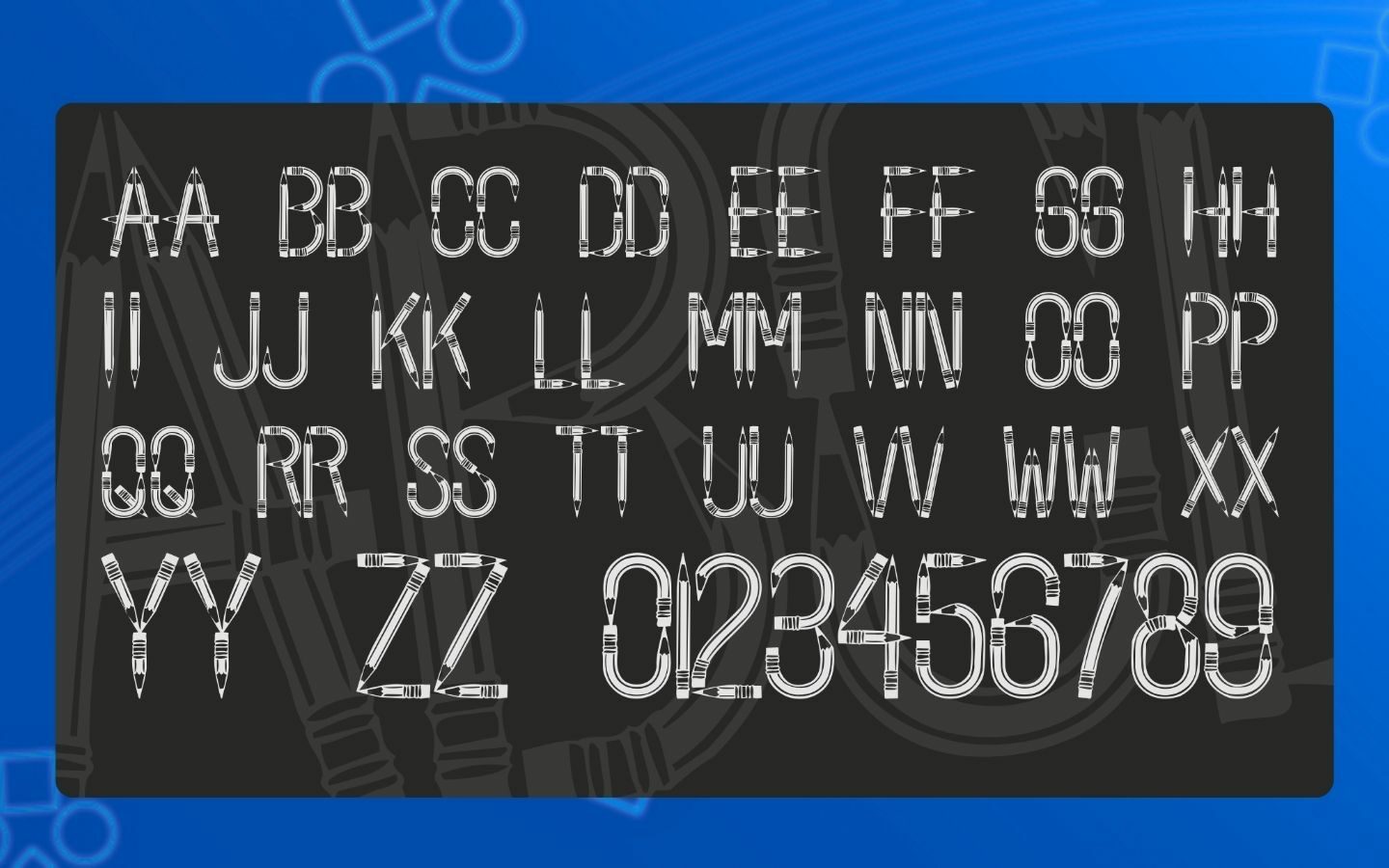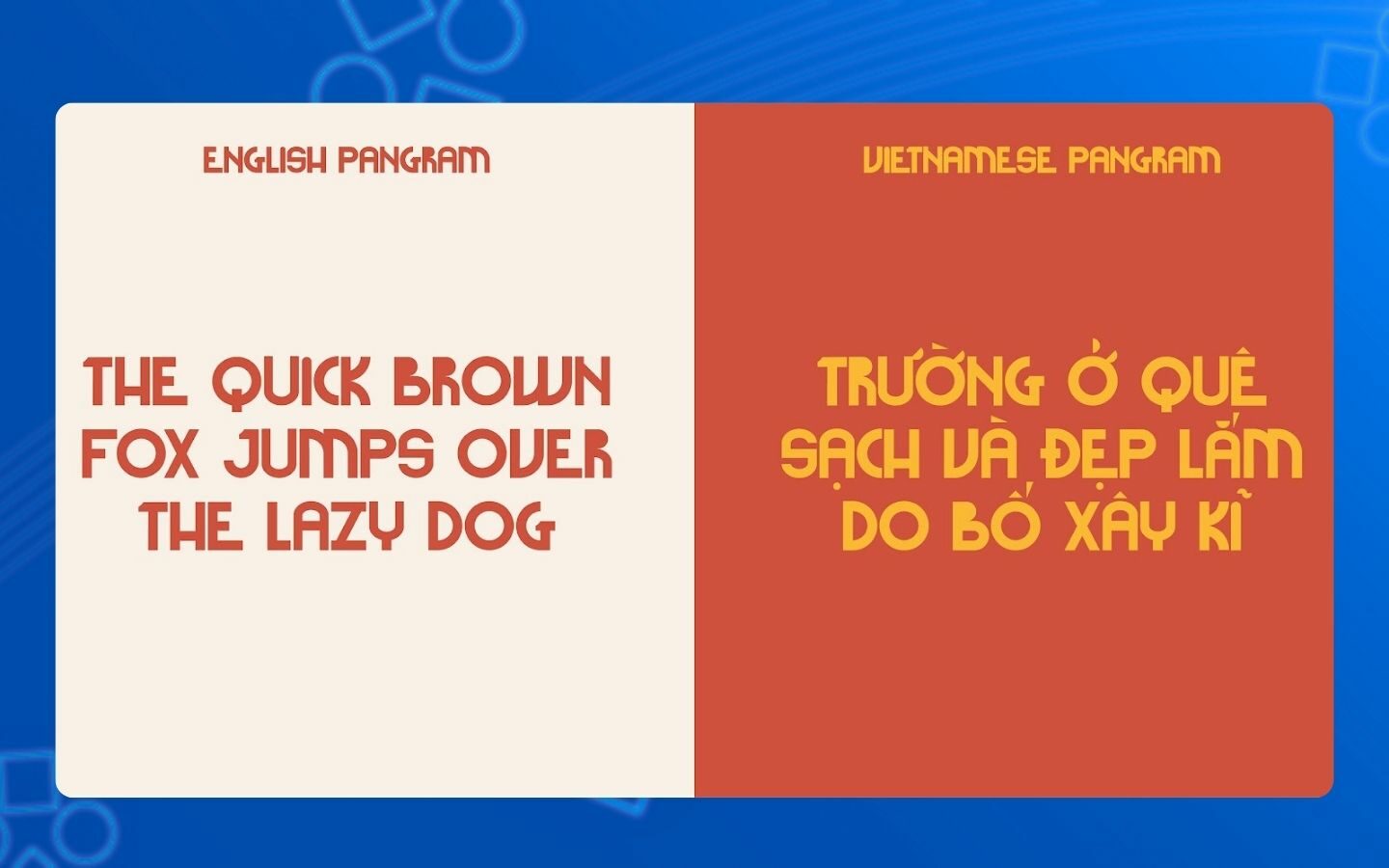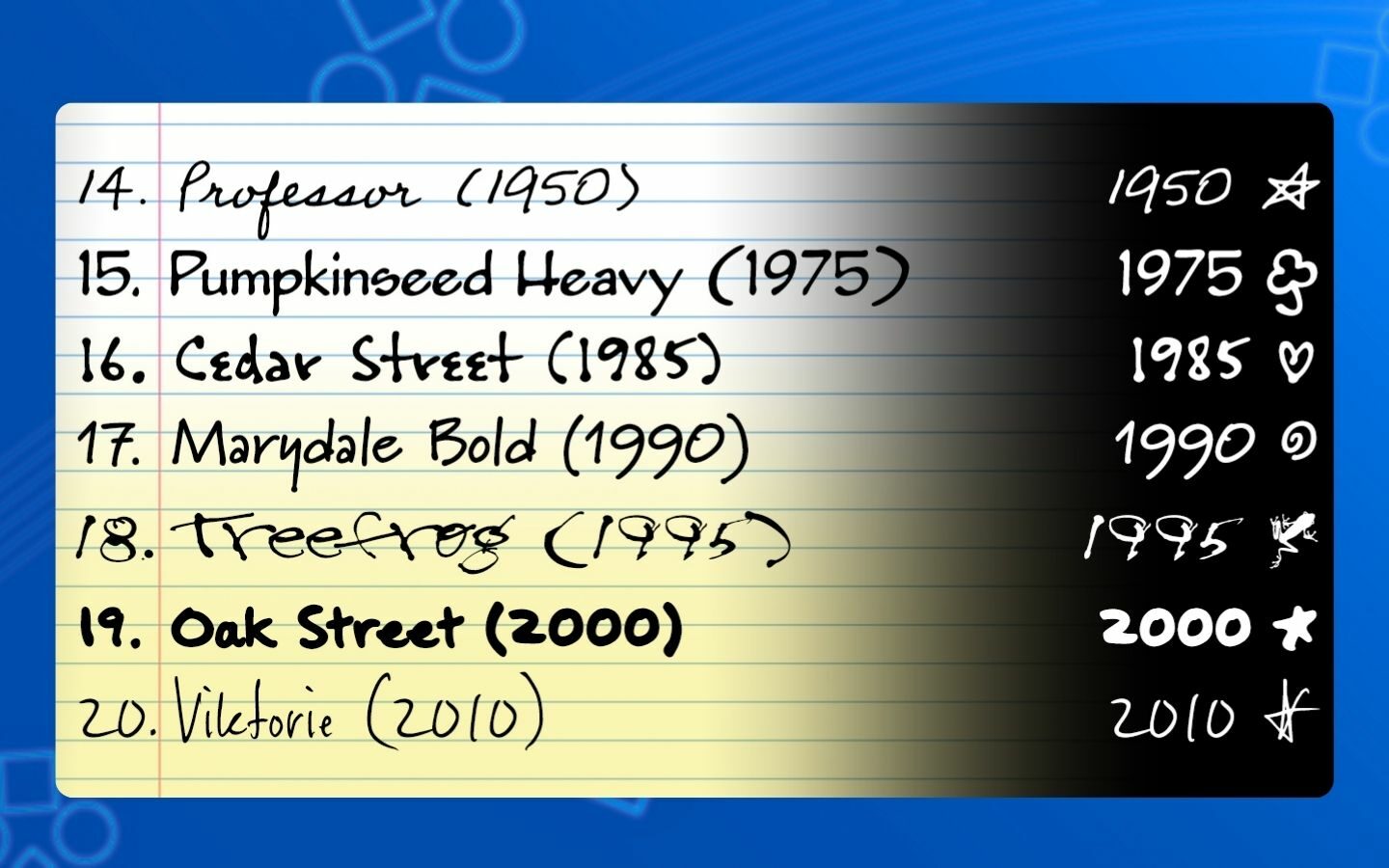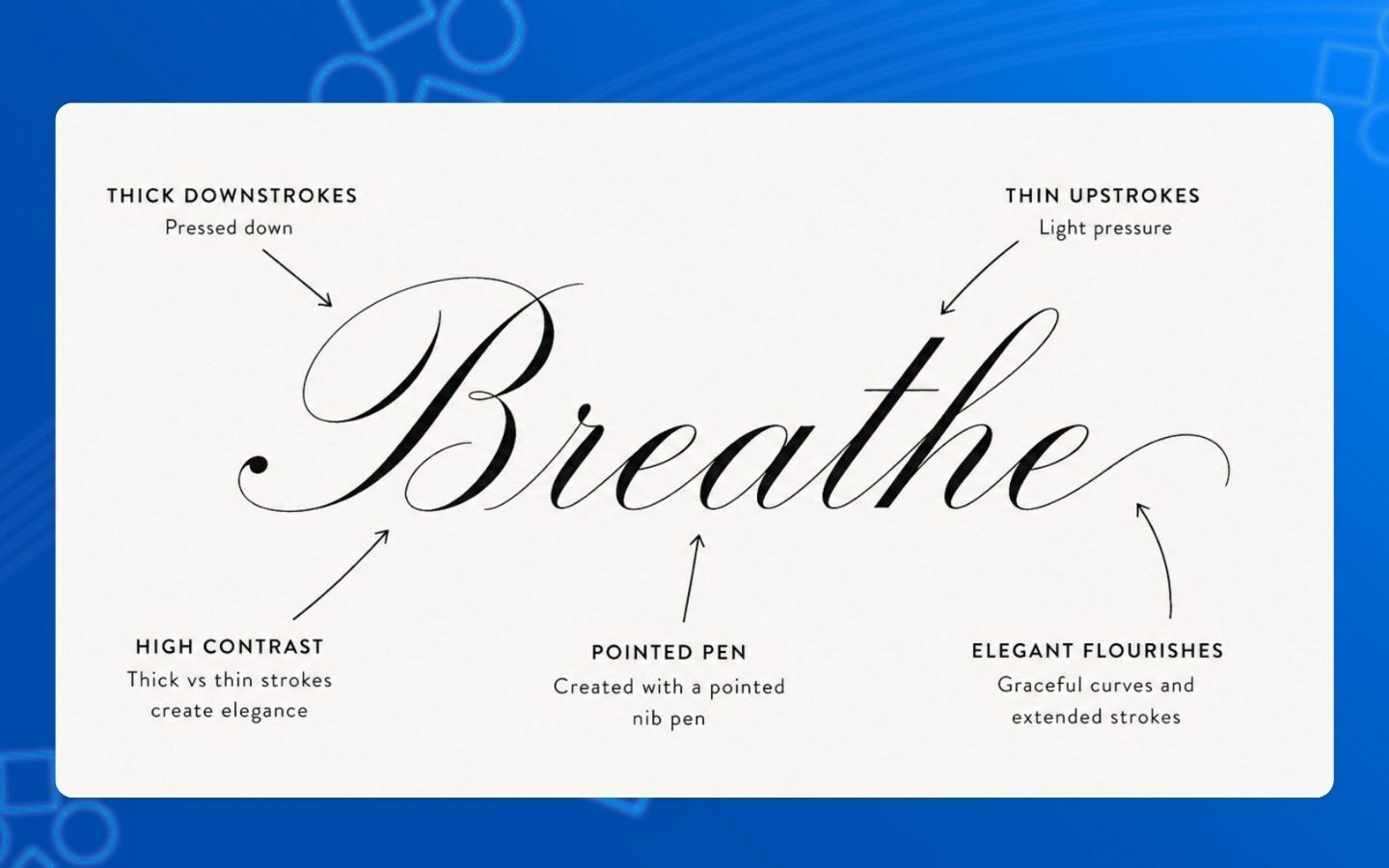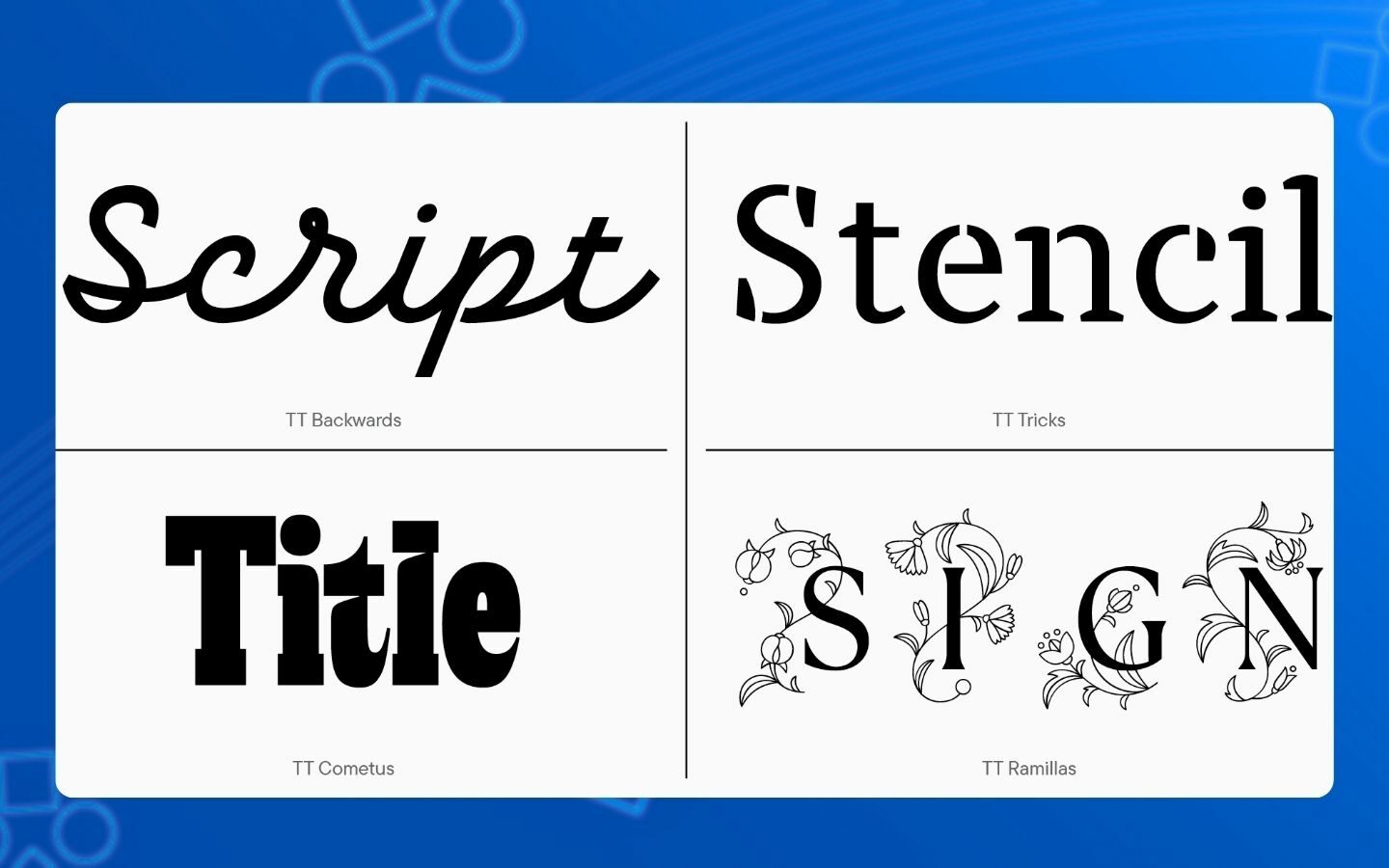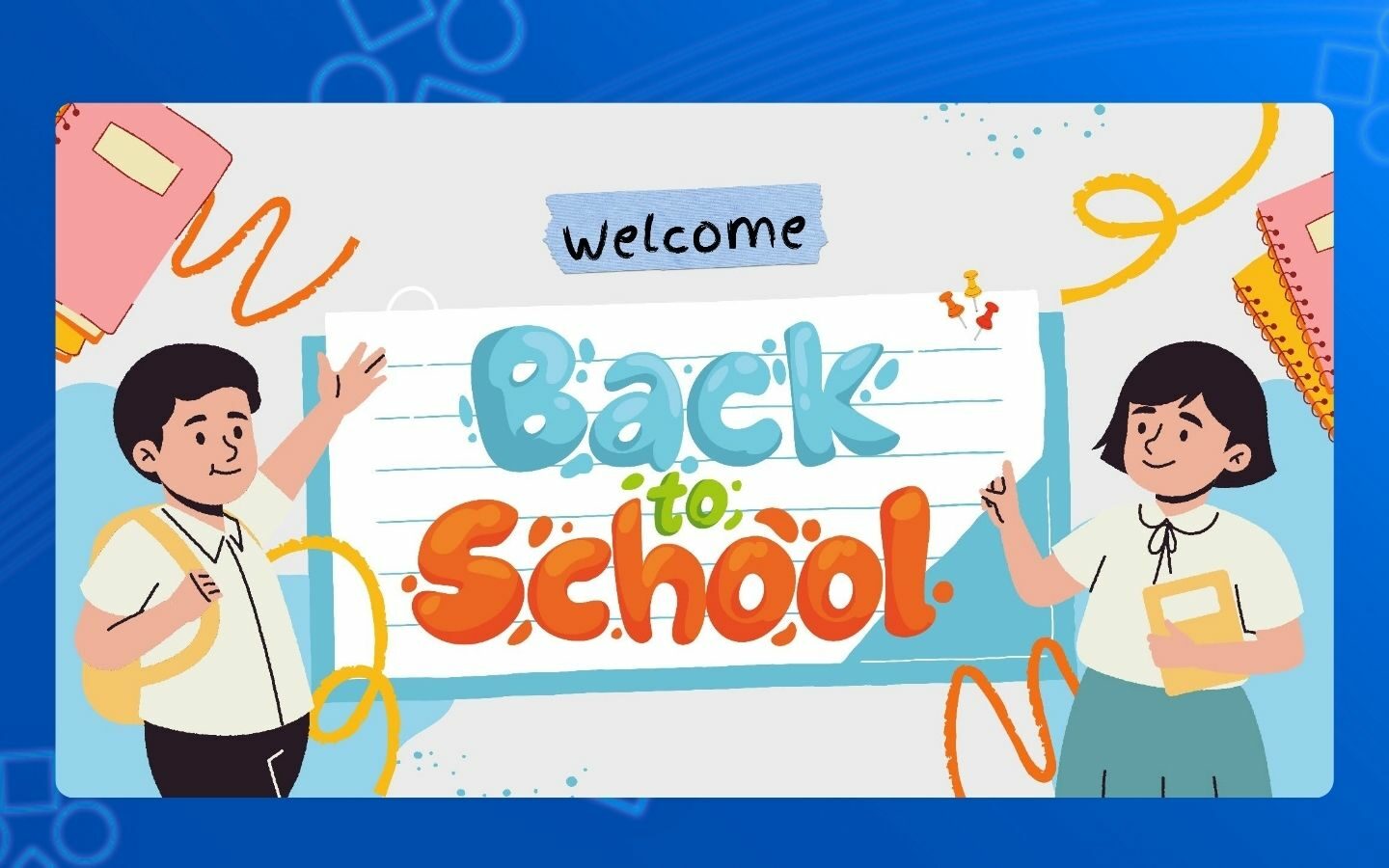
Tổng hợp font chữ Back to School đẹp nhất 2026
Mỗi dịp mùa tựu trường, nhu cầu thiết kế banner, poster, bài đăng mạng xã hội hay ấn phẩm truyền thông với chủ đề Back to School lại tăng mạnh. Để tạo điểm nhấn và truyền tải trọn vẹn tinh thần trẻ trung, năng động của năm học mới, lựa chọn font chữ phù hợp là yếu tố không thể bỏ qua. Trong bài viết này, Phong Vũ Tech News sẽ tổng hợp những font chữ Back to School đẹp, ấn tượng và phù hợp với xu hướng thiết kế 2026, giúp bạn dễ dàng tạo nên các sản phẩm thu hút học sinh, sinh viên và phụ huynh ngay từ cái nhìn đầu tiên. Cùng khám phá nhé!
I. Font chữ Back to School là gì? Cách chọn font phù hợp
Font chữ Back to School là nhóm phông chữ được thiết kế hoặc lựa chọn để tái hiện tinh thần học đường và không khí mùa tựu trường. Các font này thường lấy cảm hứng từ nét chữ viết tay, chữ phấn trên bảng, chữ trong vở hay những kiểu chữ minh họa vui nhộn, mang đến cảm giác trẻ trung, gần gũi và giàu năng lượng. Nhờ khả năng tạo điểm nhấn và truyền tải sự sáng tạo, font chữ Back to School được sử dụng rộng rãi trong thiết kế poster, banner, bài đăng mạng xã hội, tờ rơi và nhiều ấn phẩm truyền thông, giúp khơi gợi sự háo hức và hứng khởi của một năm học mới.
Font chữ Back to School tái hiện không khí học đường và mùa tựu trường
Font chữ Back to School tái hiện không khí học đường và mùa tựu trường (Nguồn: Internet)
Để lựa chọn font chữ Back to School phù hợp, bạn nên lưu ý những tiêu chí sau:
• Chọn font theo đối tượng mục tiêu: Với thiết kế dành cho trẻ mầm non hoặc tiểu học, ưu tiên các font có nét tròn, mềm mại và vui nhộn. Đối với học sinh THCS, THPT hoặc sinh viên, các font viết tay hiện đại, sans-serif cá tính hoặc kiểu chữ mang phong cách học thuật sẽ phù hợp hơn.
• Ưu tiên khả năng đọc: Font trang trí chỉ nên dùng cho tiêu đề hoặc nội dung cần tạo điểm nhấn. Phần nội dung chính nên sử dụng font đơn giản, rõ ràng để người đọc dễ theo dõi và tiếp nhận thông tin.
• Kết hợp font hợp lý: Chỉ nên sử dụng từ hai đến ba font trong cùng một thiết kế. Một font Back to School nổi bật cho tiêu đề kết hợp với một font sans-serif hoặc serif dễ đọc sẽ giúp bố cục hài hòa và chuyên nghiệp hơn.
• Đảm bảo hỗ trợ tiếng Việt: Ưu tiên các font Unicode đầy đủ để dấu tiếng Việt hiển thị chính xác. Trước khi sử dụng trong dự án chính thức, hãy kiểm tra kỹ khả năng hiển thị để tránh lỗi font làm ảnh hưởng đến chất lượng thiết kế.
II. Top 5 font chữ Back to School đẹp và đón đầu xu hướng 2026
Năm 2026, các thiết kế Back to School tiếp tục ưu tiên những font chữ trẻ trung, sáng tạo và giàu cảm hứng học đường. Dưới đây là 5 nhóm font chữ Back to School nổi bật mà bạn không nên bỏ qua:
1. Font Việt hóa
Các font Việt hóa là lựa chọn phù hợp cho những thiết kế sử dụng nhiều nội dung tiếng Việt, giúp hiển thị đầy đủ dấu và đảm bảo tính thẩm mỹ trên poster, banner hay bài đăng mạng xã hội.
Font chữ Việt hóa phù hợp cho các ấn phẩm truyền thông bằng tiếng Việt
Font chữ Việt hóa phù hợp cho các ấn phẩm truyền thông bằng tiếng Việt (Nguồn: Internet)
• iCiel Cadena: Font có nét chữ dày, bo tròn nhẹ, tạo cảm giác trẻ trung và năng động. Phù hợp để làm tiêu đề cho các chương trình khuyến mãi, sự kiện hoặc chiến dịch truyền thông mùa tựu trường.
• SVN-Androgyne: Sở hữu phong cách retro với đường nét mềm mại, gợi không khí học đường xưa. Font thích hợp cho các thiết kế mang màu sắc hoài niệm hoặc chủ đề vintage.
• UTM Cookies: Kiểu chữ tròn trịa, thân thiện và vui tươi, phù hợp với các ấn phẩm dành cho trẻ em, trường học, trung tâm giáo dục hoặc các thiết kế liên quan đến văn phòng phẩm.
2. Font chữ viết tay
Font chữ viết tay mang đến cảm giác gần gũi và tự nhiên, tái hiện nét chữ quen thuộc trên trang vở. Đây là lựa chọn phổ biến cho các thiết kế Back to School nhờ khả năng truyền tải sự trẻ trung, sáng tạo và giàu cảm xúc.
Font viết tay tái hiện nét chữ tự nhiên trên trang vở học sinh
Font viết tay tái hiện nét chữ tự nhiên trên trang vở học sinh (Nguồn: Internet)
• Caveat: Font viết tay mã nguồn mở với các ký tự có độ cao thấp tự nhiên, tạo cảm giác như ghi chép bằng tay. Phù hợp cho tiêu đề, ghi chú hoặc các thiết kế mang phong cách học đường.
• Pacifico: Sở hữu các nét chữ mềm mại và liền mạch theo phong cách brush script, giúp tiêu đề trở nên nổi bật. Font thường được sử dụng cho slogan, câu trích dẫn hoặc thông điệp truyền cảm hứng.
• Dancing Script: Kiểu chữ thanh thoát với các đường nét uyển chuyển, tạo cảm giác năng động và hiện đại. Font phù hợp với poster, banner hoặc bài đăng mạng xã hội dành cho mùa tựu trường.
3. Font chữ nét thanh nét đậm
Nhóm font nét thanh nét đậm phù hợp với các thiết kế cần sự chỉn chu, chuyên nghiệp nhưng vẫn giữ được nét trẻ trung của chủ đề học đường. Đây là lựa chọn lý tưởng cho các ấn phẩm mang tính học thuật hoặc sự kiện của nhà trường.
Font nét thanh nét đậm phù hợp cho thiết kế Back to School chuyên nghiệp
Font nét thanh nét đậm phù hợp cho thiết kế Back to School chuyên nghiệp (Nguồn: Internet)
V. Tổng kết
Mùa tựu trường luôn là thời điểm sôi động cho các chiến dịch truyền thông và những ý tưởng thiết kế mới. Font chữ Back to School phù hợp sẽ giúp poster, banner hay bài đăng mạng xã hội truyền tải trọn vẹn tinh thần học đường, tạo ấn tượng với học sinh, sinh viên và phụ huynh. Hy vọng bài viết đã mang đến cho bạn những gợi ý hữu ích để lựa chọn font chữ phù hợp cho các thiết kế Back to School 2026. Và đừng quên theo dõi Phong Vũ Tech News để cập nhật thêm nhiều xu hướng thiết kế, công nghệ và thủ thuật hữu ích mới nhất nhé!